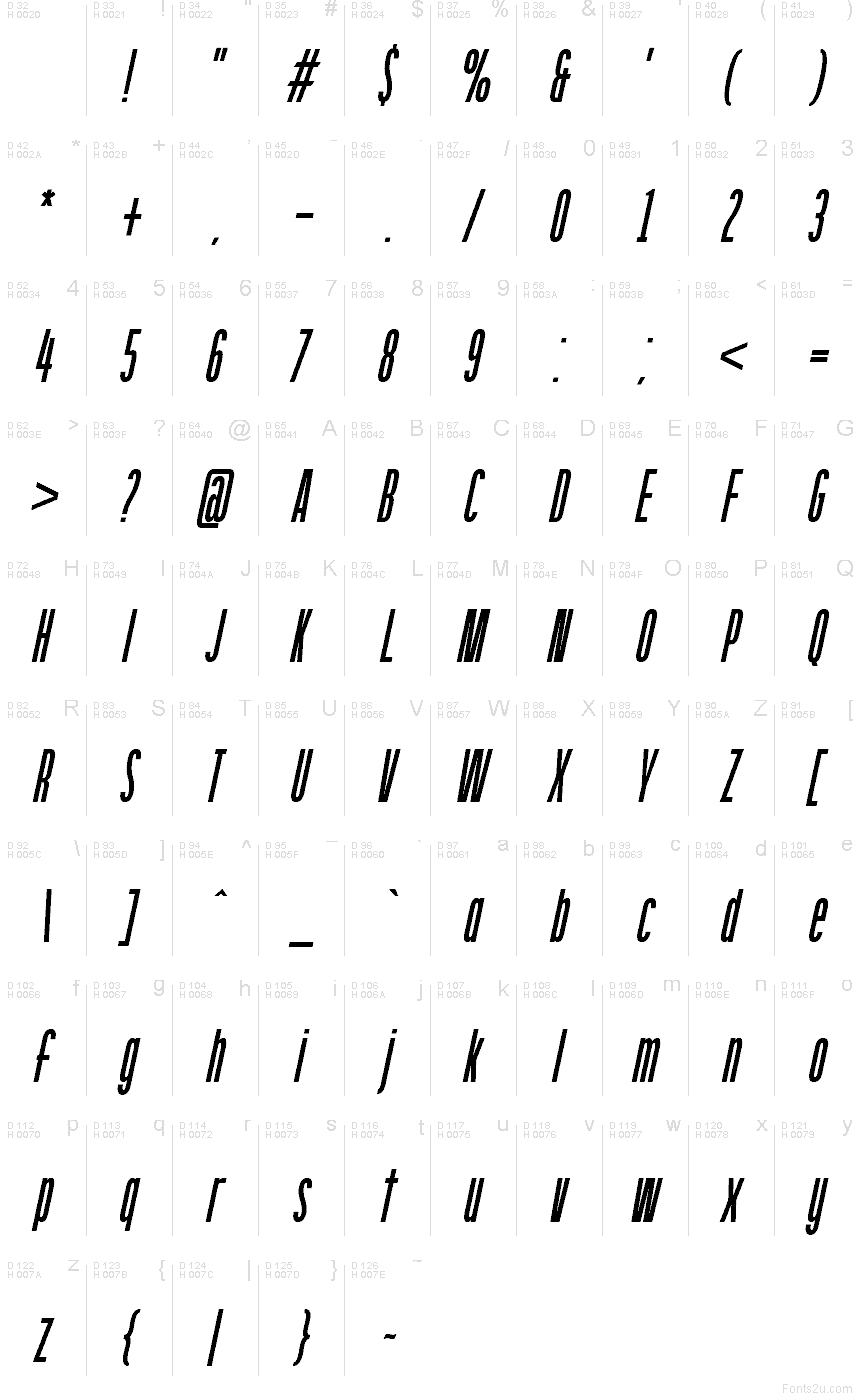
Il carattere Gantura Italic di Muhamad Fikry Nuralif (Fikryal Studio) si fa notare per il suo taglio rapido e sportivo, con una struttura sans serif pulita che resta leggibile anche quando l'energia del design è al massimo. I tratti sono nitidi e leggermente condensati, conferendo una spinta dinamica alle parole senza mai comprometterne la forma. Parte della famiglia Gantura, è un font corsivo moderno e gratuito che unisce movimento e carattere in un unico segno distintivo.
Usa Gantura Italic per dare incisività a loghi, grafiche fitness e streetwear, poster automobilistici o di ciclismo, callout per prodotti tech, titoli e-sport, packaging e advertising social che richiedono velocità. Impostalo leggermente più grande sulle righe brevi per far respirare l'inclinazione e abbinalo a un sans dritto della famiglia Gantura per il testo principale, mantenendo così un contrasto netto. Questo font gratuito brilla quando cerchi urgenza senza confusione.